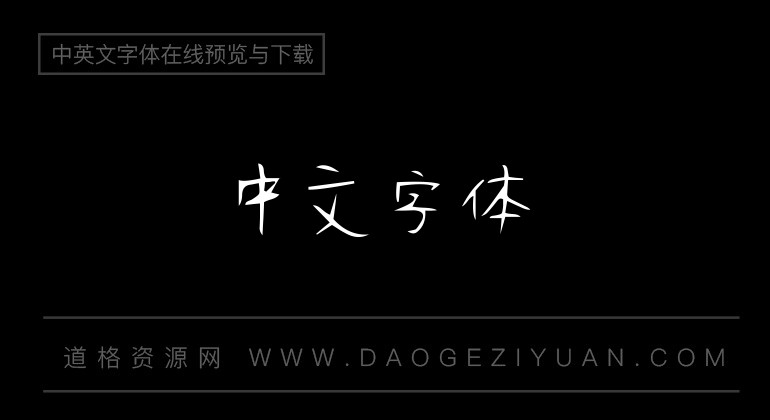
逐浪大雪钢笔体
逐浪大雪钢笔体是一款精致大气的楷体字体,具有较强的笔画细腻度,每一个字符都有着深厚的文化底蕴,十分适合拿来用于大型活动宣传、节日祝福等场合。它的字形比较挺拔,比较端正,比较有秩序,整体显得非常大气,拥有较强的视觉冲击力,能够让观众一眼就能够记住,具有较强的宣传力。
逐浪大雪钢笔体是一款非常不错的手写艺术字体,具有很好的视觉感,适合于文化类的宣传设计、商业类品牌的广告和产品包装设计以及个性化文字排版等较多场景。
逐浪大雪钢笔体字符映射图